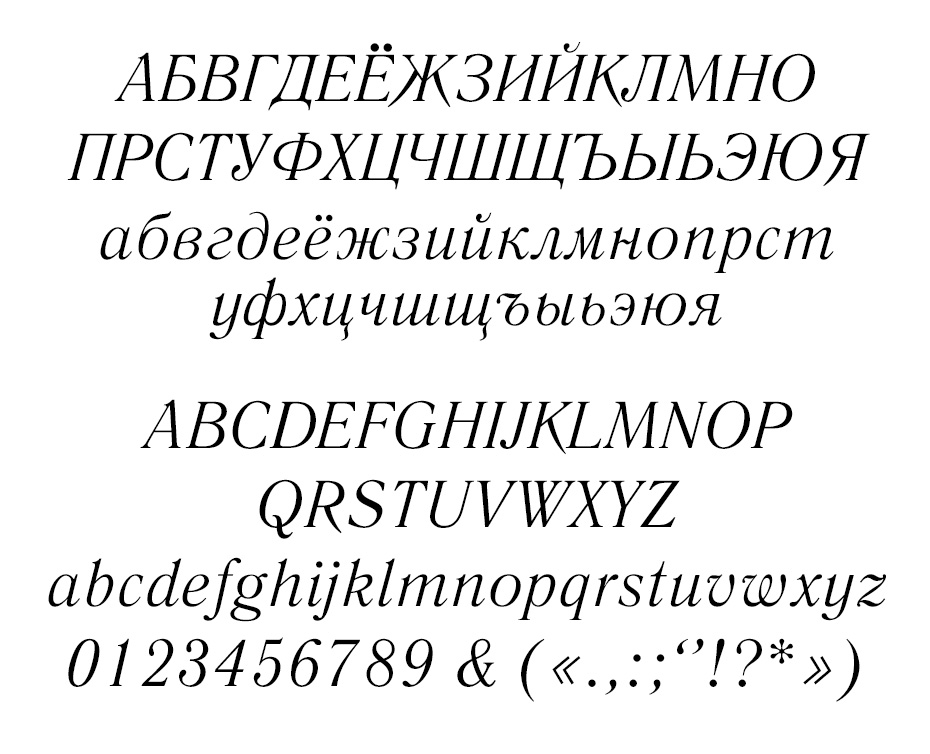
От А до Я.
Русский шрифтЛиля Пальвелева: Разговор об истории русского шрифта уместно начать с древних финикийцев. Именно они изобрели в XI веке до нашей эры самый первый буквенно-звуковой алфавит, ставший прообразом многих алфавитов мира, в числе прочих – русского. Правда, заимствование знаков произошло не напрямую, а через графику греков. Кириллица была создана все-таки на основе древнегреческих букв, чрезвычайно ясных, удобных и для запоминания, и для начертания. В их основе геометрические простые формы – круг, квадрат, треугольник. Тут сказалось математическое чутье греков и их безупречный художественный вкус.
Лингвисты, рассуждая об алфавитах, говорят о способах фиксации звучащей речи. Но есть люди, для которых шрифт того или иного языка представляет интерес совсем другого рода. Архитектор Андрей Чернихов рассказывает об изысканиях своего деда, тоже архитектора Якова Чернихова.
Андрей Чернихов: Им было подготовлено к печати ( а издана только одна пятая часть) 50 трудов в области построения классического шрифта.
Это фундаментальный труд, когда он, кстати, с помощью моей мамы, а своей дочери, сделал 144 таблицы (каждая таблица 55 на 77 сантиметров) с анализом построения того или иного шрифта той или иной эпохи того или иного народа, включая и эфиопский шрифт, включая русские шрифты, и старорусские шрифты, и елизаветинский, и клинопись. Потому что обнаружил в них определенные закономерности. Буквально таким внутренним интеллектуальным исчислением обнаружил эти закономерности, ручным образом показал, что же такое каждый шрифт (а шрифт – это уже часть текста, это графика языка). Он как бы вскрывал код, геометрический код, построения шрифтов как азбук тех или иных народов, что само по себе требует отдельного описания. Он не мог, естественно, и не собирался описывать всю глубину своей работы. Он ее делал как интуитивист.
Лиля Пальвелева: Однако кое-какие тонкие наблюдения Яков Чернихов все же сделал. К примеру, он подметил, что шрифт несет в себе память о материале, о том с помощью чего и на что наносились когда-то знаки.
Но главное в труде Якова Чернихова это, конечно, таблицы шрифтов. Им более полувека, однако эти таблицы недаром показывают на современных выставках графического дизайна. Каждый лист – самостоятельное произведение искусства, столь выразительны и безупречны линии букв, выведенные рукой мастера. Да, он воспроизводил образцы ушедших эпох, но не копировал их слепо, а именно воспроизводил. Вот характерный отклик в прессе по поводу одной из таких выставок.
«Его русский шрифт отличается элегантностью, почти немыслимой для кириллицы. В черниховском шрифте есть благородство антиквы, соединенное с какой-то гордой нервностью, как будто речь идет о той классике, которая уже знает об итоговой победе варваров».
Лиля Пальвелева: Каждая буква Якова Чернихова помещена в прямоугольник, покрытый тонкой сеткой линий. Рядом какие-то цифры и формулы. Андрей Чернихов поясняет:
Андрей Чернихов: Это уже инструментарий. Без построения, без сопряжения… Напоминаю тем, кто забыл среднюю школу, что сопряжение – это соприкосновение двух или более кривых. Они должны сойтись в точку так плавно и незаметно, что человеческий глаз не замечает изменения дуги кривой. Отсюда буква Я, или буква Р, или буква С. Они могут иметь до 10-15-20 сопряжений. Так много кривых образуют одну единственную букву. Так вот простроив каждую букву и в членениях… Членения, как известно, фиксировались партами и секундами. Это латинское обозначение тонких пропорций и тонких членений элементов, будь то архитектура, будь то буква. Так вот, вот это сочетание улавливания линейных пропорций – прямоугольники – в системе координат. Просто надо задать систему координат, в которую вписывается буква.
Хотя это не означает, что все буквы идеально вписываются в прямоугольники. Но для того, чтобы исчислить закон построения буквы, нужно наложить некую формальную структуру геометрическую, через которую ты можешь сделать эти исчисления, как графические, так и чисто арифметические.